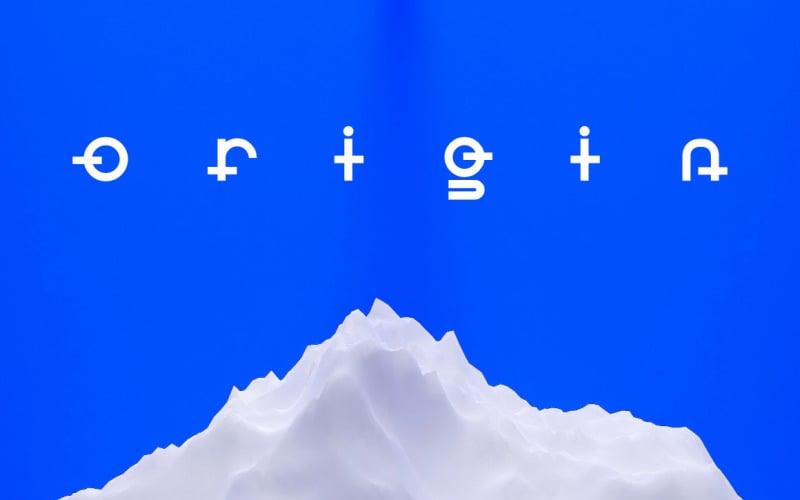
دانلود فونت Getboreg Minus Tech – Glitch Font
یک فونت پیشرفته sans-serif که با دقت برای نسلی که در زمینه فناوری کار می کنند ساخته شده است. طرح های خود را در تلفیقی یکپارچه از مینیمالیسم براق و جذابیت فریبنده هنر glitch غوطه ور کنید.
ویژگی های کلیدی Getboreg Minus Tech :
• طراحی با بالاترین استاندارد جهانی
• مناسب برای انواع طرح ها و پروژه های گرافیکی